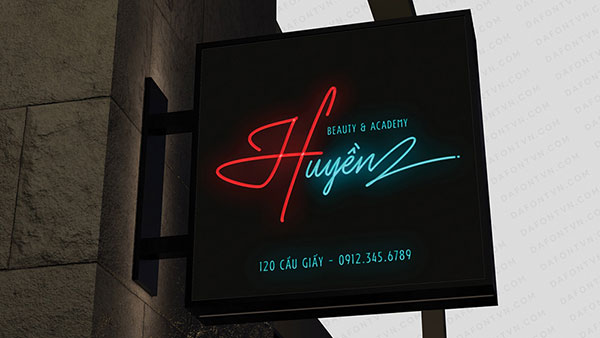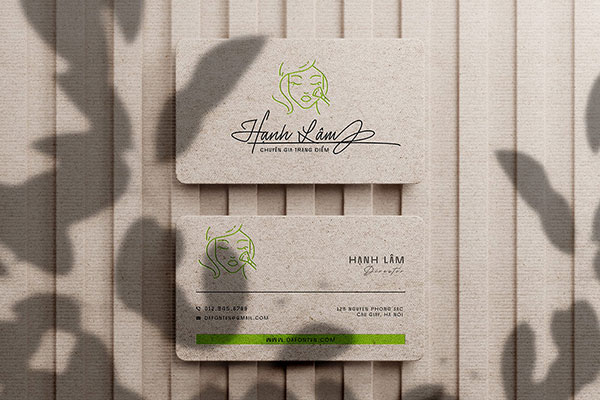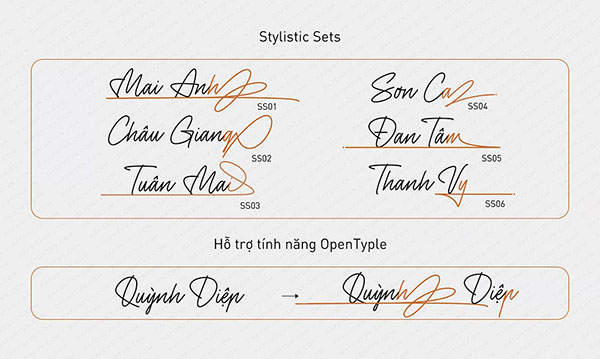
Download Font Chữ Sarion Miễn Phí
1. Font Chữ Việt Hóa Sarion Là Gì?
Font chữ Việt hóa Sarion là một loại font chữ được thiết kế đặc biệt để hỗ trợ đầy đủ các ký tự tiếng Việt, bao gồm cả dấu và các ký tự đặc trưng. Với phong cách hiện đại, tinh tế, font Sarion mang lại sự chuyên nghiệp và thẩm mỹ cao trong các thiết kế đồ họa, in ấn, và trình bày văn bản.
Font chữ này có cảm giác gọn gàng và mượt mà, chắc chắn sẽ tạo nên điểm nhấn cho bất kỳ thiết kế nào mà bạn sử dụng. Nó hoàn hảo cho nhiều dựán khác nhau như logo, xây dựng thương hiệu, thiệp mời, chữ ký, nhãn mác, nhiếp ảnh, và nhiều hơn thế nữa!
2. Chức Năng Đặc Biệt Của Font Chữ
Font chữ không chỉ đơn thuần là yếu tố thẩm mỹ trong thiết kế, mà còn đóng vai trò quan trọng trong việc truyền tải thông điệp và cảm xúc của nội dung.
• Tính dễ đọc: Mỗi loại font chữ đều mang một đặc trưng riêng, từ sự trang trọng, chuyên nghiệp đến sự sáng tạo, thân thiện. Sarion được thiết kế với độ dày và độ cao chữ hợp lý, giúp người đọc dễ dàng nhận diện chữ cái và từ ngữ. Điều này đặc biệt quan trọng trong việc truyền tải thông điệp một cách rõ ràng.
• Thẩm mỹ cao: Sarion mang đến vẻ đẹp hiện đại và sang trọng. Các đường nét uốn lượn, cùng với sự cân đối giữa các ký tự, tạo nên một tổng thể hài hòa, phù hợp cho nhiều loại hình thiết kế như poster, brochure, hay website.
• Hỗ trợ ngôn ngữ đa dạng: Không chỉ hỗ trợ tiếng Việt, Sarion còn có khả năng hiển thị tốt với nhiều ngôn ngữ khác, giúp mở rộng phạm vi sử dụng cho các dự án quốc tế.
• Chức năng đặc biệt của font chữ nằm ở khả năng tạo sự nhận diện thương hiệu. Nó giúp tăng cường trải nghiệm người dùng và hỗ trợ việc truyền đạt thông tin một cách hiệu quả.